Будущее шрифтов: как ИИ влияет на типографику
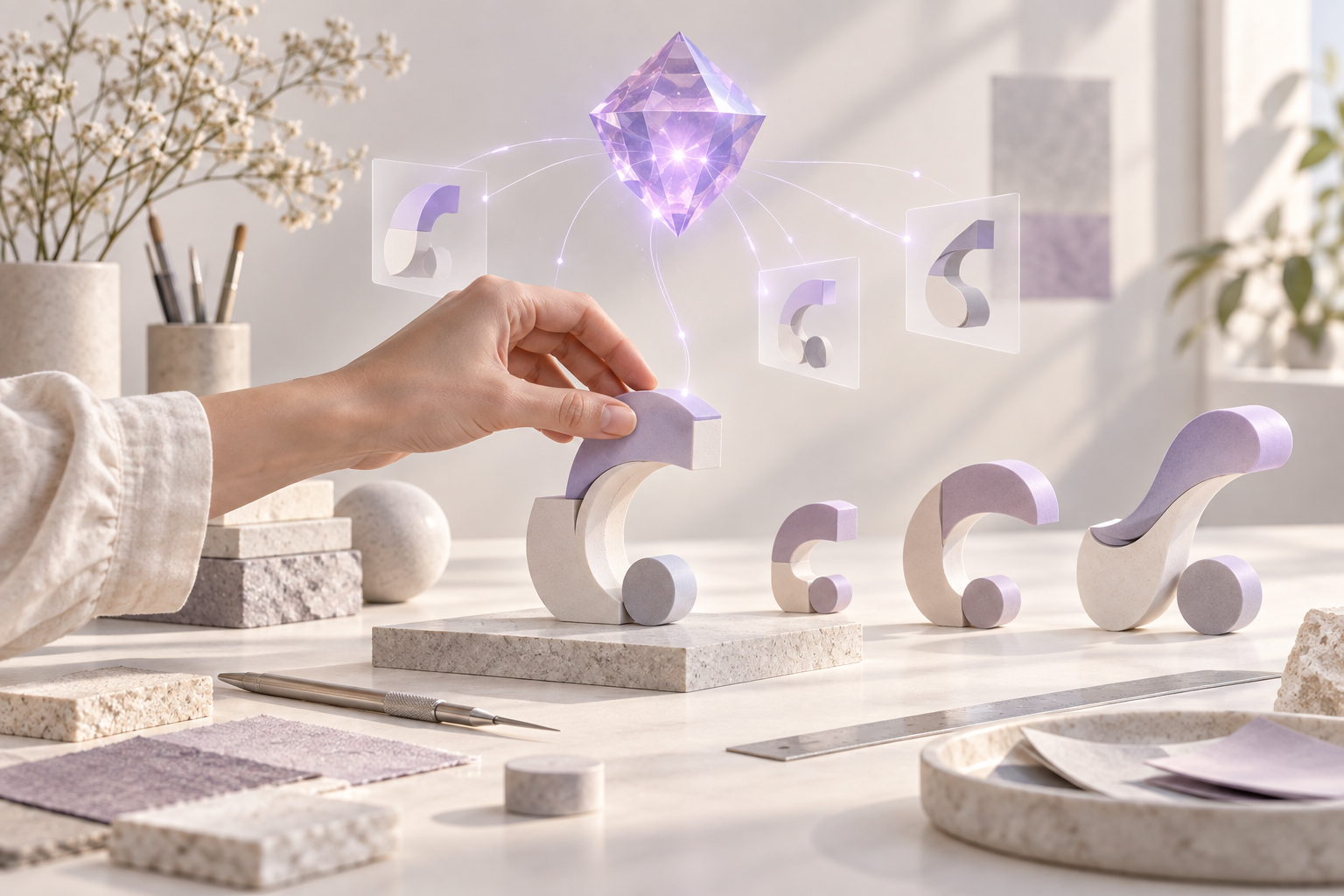
ИИ уже влияет на типографику не как замена шрифтовому дизайнеру, а как инструмент для генерации вариантов, анализа читаемости и настройки гарнитур под разные экраны. В ближайшем будущем ценность будет создавать связка алгоритмов и человека: ИИ ускоряет рутинные операции, а дизайнер отвечает за характер, культурный контекст, качество кириллицы и уместность решения.
Дата актуальности: 20 сентября 2026 года. Ниже рассмотрены устойчивые направления развития, которые уже заметны в цифровом дизайне и не зависят от конкретной версии сервиса или модели.
Что именно меняет ИИ в работе со шрифтом
Традиционная разработка гарнитуры требует последовательной работы с формами знаков, пропорциями, интервалами, насыщенностью, языковыми наборами и тестовыми текстами. ИИ способен ускорить этот процесс: предложить несколько направлений, найти похожие визуальные закономерности, выявить конфликтующие интервалы и подготовить материал для дальнейшей ручной доработки. Но итоговый шрифт по-прежнему нуждается в редактуре и проверке.
Генерация вариантов вместо одного готового решения
Алгоритм удобно использовать на этапе поиска. Например, дизайнеру нужен гуманистический гротеск для сервиса доставки: нейросеть может помочь сформулировать несколько направлений — более открытые формы, мягкие окончания штрихов, компактный набор для интерфейсов или выразительная версия для рекламных заголовков. Такой результат нельзя считать готовым шрифтом. Это визуальный черновик, который помогает быстрее сравнить идеи и выбрать направление.
Настройка интервалов, кернинга и насыщенности
В шрифте важны не только очертания букв, но и отношения между ними. Пара «Т» и «о», сочетания с кавычками, цифрами или знаками валюты требуют разных интервалов. ИИ может подсветить подозрительные пары и предложить первичную настройку, однако оптическое расстояние не всегда совпадает с математическим. Финальная оценка должна выполняться на реальных словах, заголовках и интерфейсных строках.
Адаптация гарнитуры к экрану и контексту
Цифровая типографика всё чаще работает в разных условиях: на компактном смартфоне, широком мониторе, в навигации, на упаковке или в рекламном баннере. ИИ может помогать находить настройки для разных размеров и плотности текста. Например, для мелкого интерфейсного текста потребуются более открытые внутренние просветы и устойчивые формы, а для крупного заголовка допустимы контраст и более заметная индивидуальность.
Где искусственный интеллект действительно полезен дизайнеру
Практическая ценность ИИ проявляется там, где нужно быстро обработать много вариантов или проверить систему знаков по понятным критериям. Чем точнее поставлена задача, тем полезнее результат. Запрос «сделай красивый шрифт» слишком расплывчат, а описание назначения, аудитории, языков, носителей и ограничений даёт дизайнеру основу для осмысленного отбора.
- Сформировать несколько направлений начертания перед ручной разработкой.
- Проверить, как меняется восприятие текста при разной насыщенности и ширине.
- Найти проблемные сочетания знаков в кириллице, латинице и цифрах.
- Подготовить тестовые строки для интерфейса, упаковки и рекламных материалов.
- Сравнить версии гарнитуры по читаемости, плотности и визуальному характеру.
- Автоматизировать повторяющиеся операции при подготовке набора символов.
Особенно полезен ИИ в работе с большими наборами символов. Если проект требует кириллицу, латиницу, цифры, математические знаки и несколько языковых вариантов, алгоритмическая проверка помогает заметить несогласованность раньше. Но наличие всех глифов ещё не означает качество: нужно проверить единообразие конструкции, ударения, кавычки, тире, знаки валют и реальные языковые сочетания.
Практический сценарий: от идеи до рабочего шрифта
Рассмотрим типичный проект: нужна фирменная гарнитура для онлайн-сервиса с мобильным приложением. Шрифт должен хорошо читаться в коротких кнопках, поддерживать русский и английский языки, иметь заметный характер в заголовках и не перегружать экран в длинных описаниях. ИИ здесь работает как помощник на этапах исследования, генерации и проверки, но не принимает решение за команду.
- Определите задачу. Зафиксируйте носители, размеры текста, языки, аудиторию и эмоциональное впечатление, которое должна создавать гарнитура.
- Соберите направления. С помощью ИИ подготовьте несколько описаний и визуальных подходов: нейтральный гротеск, гуманистическая версия или более геометричный вариант.
- Проверьте систему знаков. Сравните кириллические и латинские формы, цифры, знаки препинания, кавычки, тире и символы интерфейса.
- Настройте текстовый набор. Проверьте интервалы, кернинг, насыщенность и длину строк на реальных экранах приложения.
- Проведите ручную редактуру. Исправьте неоднозначные формы, слабые просветы, неравномерный ритм и несоответствия между языками.
- Сделайте прикладной тест. Поместите шрифт в макеты кнопок, карточек, уведомлений, заголовков и длинных текстов, затем сравните версии.
Будущее шрифтов связано не с исчезновением дизайнера, а с переходом от статичной гарнитуры к более гибкой типографической системе. ИИ ускоряет рутинные операции и помогает исследовать варианты, но качество определяют человеческая редактура, внимание к кириллице, проверка на реальных сценариях и ясные правила применения.